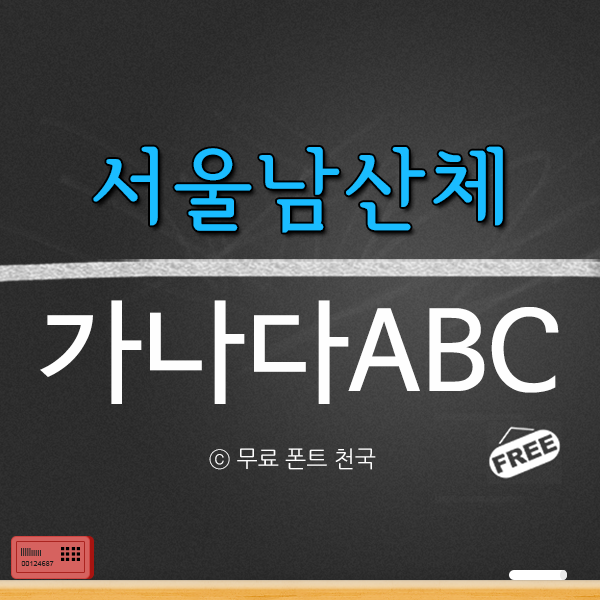
절제된 스타일의 서울남산체 한글폰트
서울남산체 폰트 정보
서울남산체는 서울시에서 무료로 배초하는 서체입니다. 글자와 글자 사이에 넓은 여백을 확보해 가독성과 시안성을 넓혔으며, 한국적 곡선을 사용하여 정체성을 표현 했습니다. 비 대칭적 'ㅅ' 형태로 글자의 동세를 강조하고 자폭을 줄여 여유로운 공간을 형성했습니다. 서울한강체가 붓글씨 느낌이 드는 서체라면 서울남산체는 바른고딕 스타일에 매그러운 느낌을 잘 전달하는 서체입니다. 서울한강체와 더불어 누구나 자유롭게 무료로 사용 가능하며 별도의 서체를 구매하지 않아도 기업, 공공기관과 단체 등에서 저작권 걱정 없이 사용 가능합니다.
서울남산체 폰트 # 미리보기
12~80PT 크기로 가독성을 테스트 해본 서울남산체 폰트
100PT 크기 이상으로 작업한 오버레이 효과를 적용한 서울남산체 폰트
100PT 크기 이상으로 그레이언트를 효과를 적용한 서울남산체 폰트